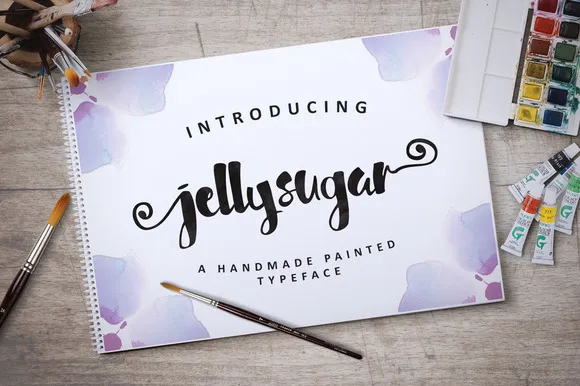
Jellysugar Typeface – Download Grátis
Jellysugar é uma delicada tipografia brush script que transmite naturalidade com sua aparência handmade. Inspirada em traços de pincel trabalhados a mão, esta fonte oferece um visual autêntico e elegante perfeito para criar texto reluzente e sofisticado. O seu conjunto consiste em 257 gíliptas, além de alternativas de caracteres, que proporcionam uma experiência completa com recursos do tipo opentype. Este script é perfeito para designers buscando adicionar um toque único e artesanal aos seus projetos gráficos, seja em cartazes publicitários, editoriais de revistas ou até mesmo no design de interfaces de aplicativos. Jellysugar não apenas oferece uma aparência natural e autêntica, mas também adiciona um ar de sofisticação a qualquer texto que ela envolve.